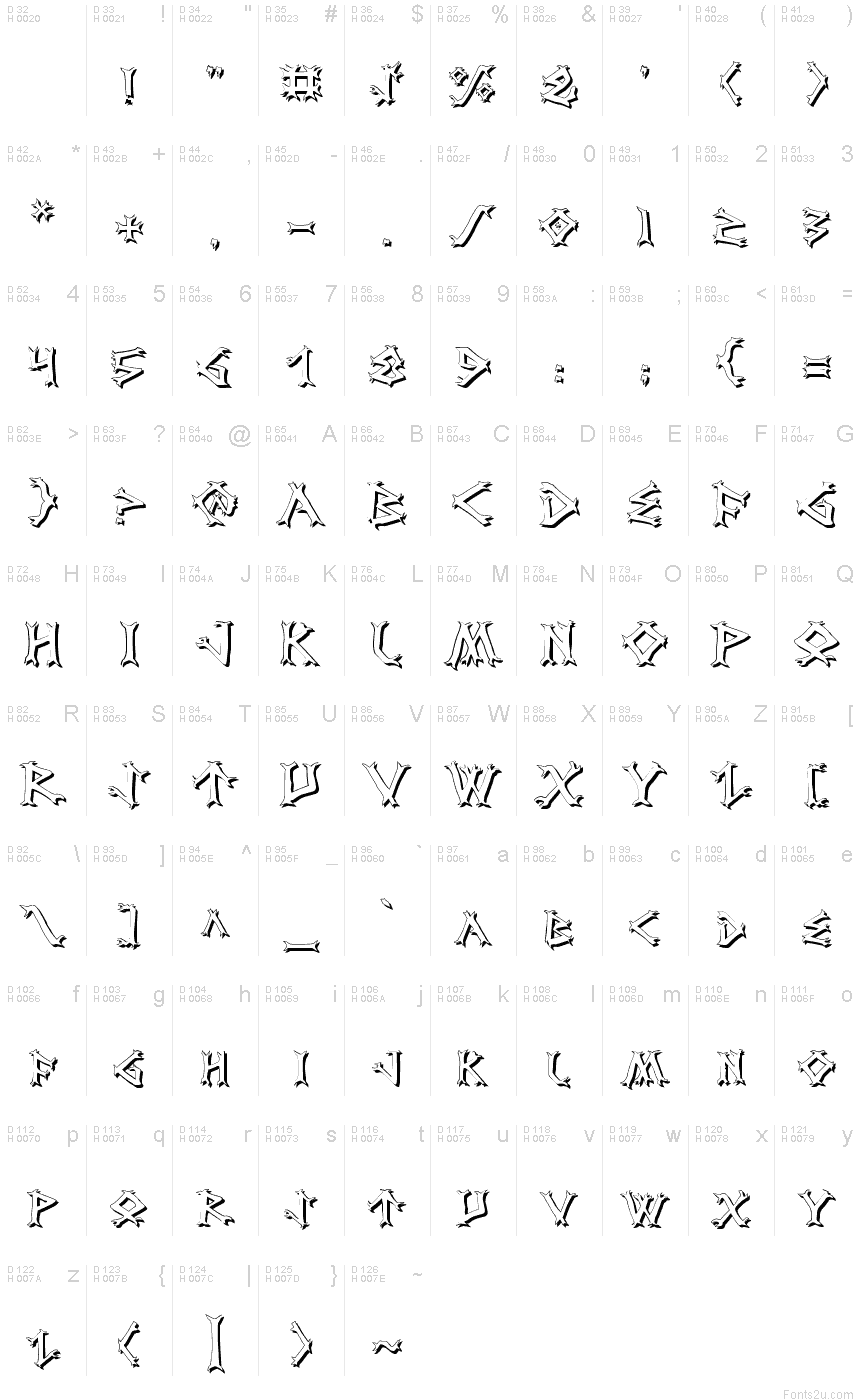
Dragon Order Shadow di Iconian Fonts è un carattere fantasy gratuito che sembra inciso dagli artigli di un drago. Ogni lettera è frastagliata e appuntita, con un'ombra interna scura che conferisce alle forme un effetto scolpito e tridimensionale. I tratti si contorcono e si allargano come i bordi di una pergamena bruciata, regalando ai titoli un'energia drammatica e arcana che cattura l'attenzione su ogni pagina o schermo.
Con Dragon Order Shadow puoi dare una voce mistica e coerente a giochi fantasy, manuali RPG, loghi di band metal, banner per convention, poster LARP o miniature YouTube dai temi dark. Questo font gratuito eccelle nelle grandi dimensioni, dove i suoi bordi ruvidi e le ombre interne rimangono nitidi e leggibili. Per il testo di accompagnamento, abbinalo a un sans serif geometrico pulito e più leggero per mantenere la leggibilità dell'impaginazione, mentre il titolo fa tutto il lavoro magico.